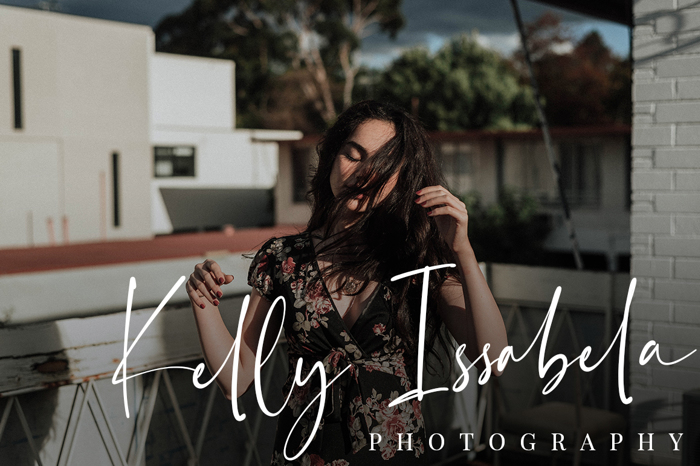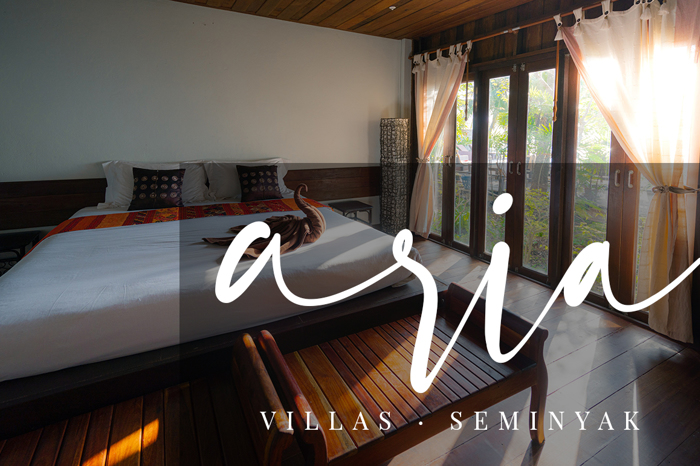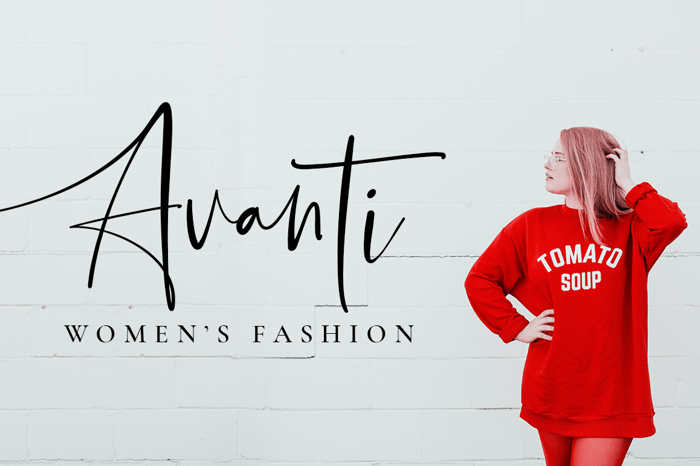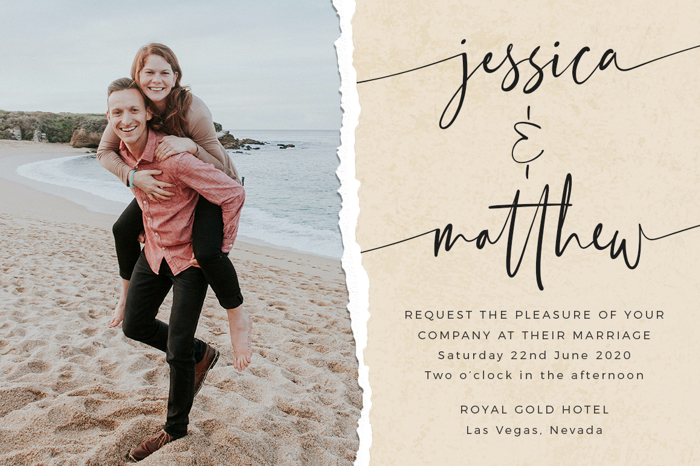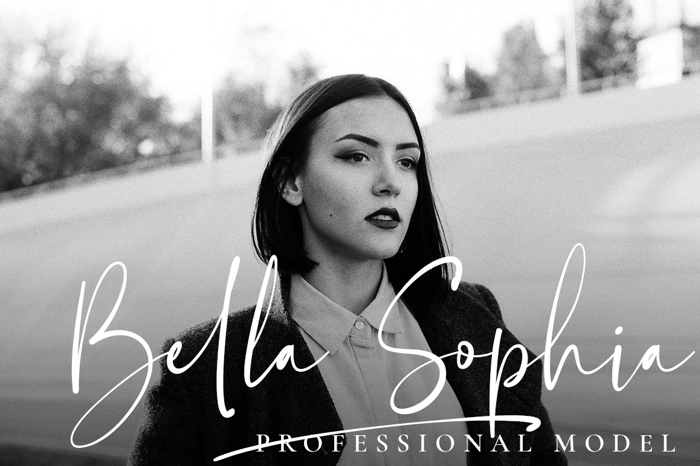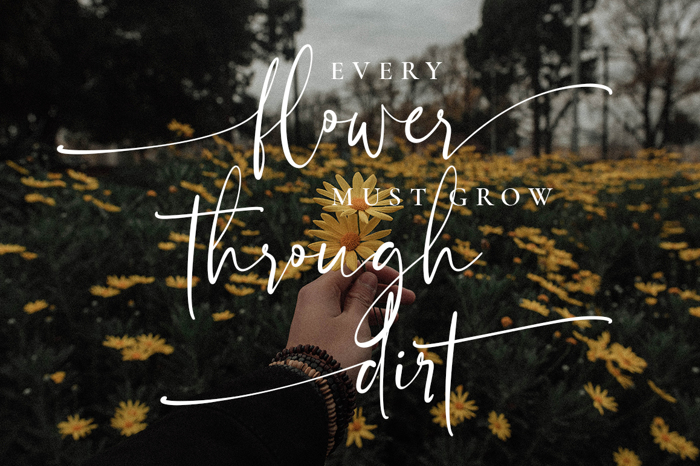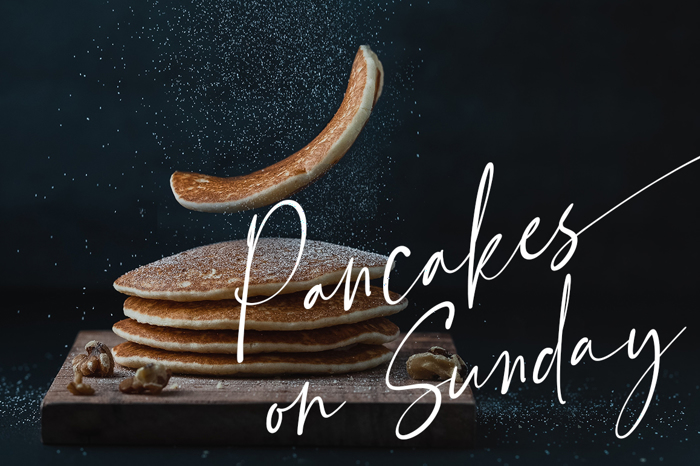
Florentea – очаровательный и элегантный шрифт. Он будет выглядить потрясающе на свадебных приглашениях, открытках, цитатах, логотипах, визитных карточках и любом другом дизайне.
Автор: Typesthetic Studio